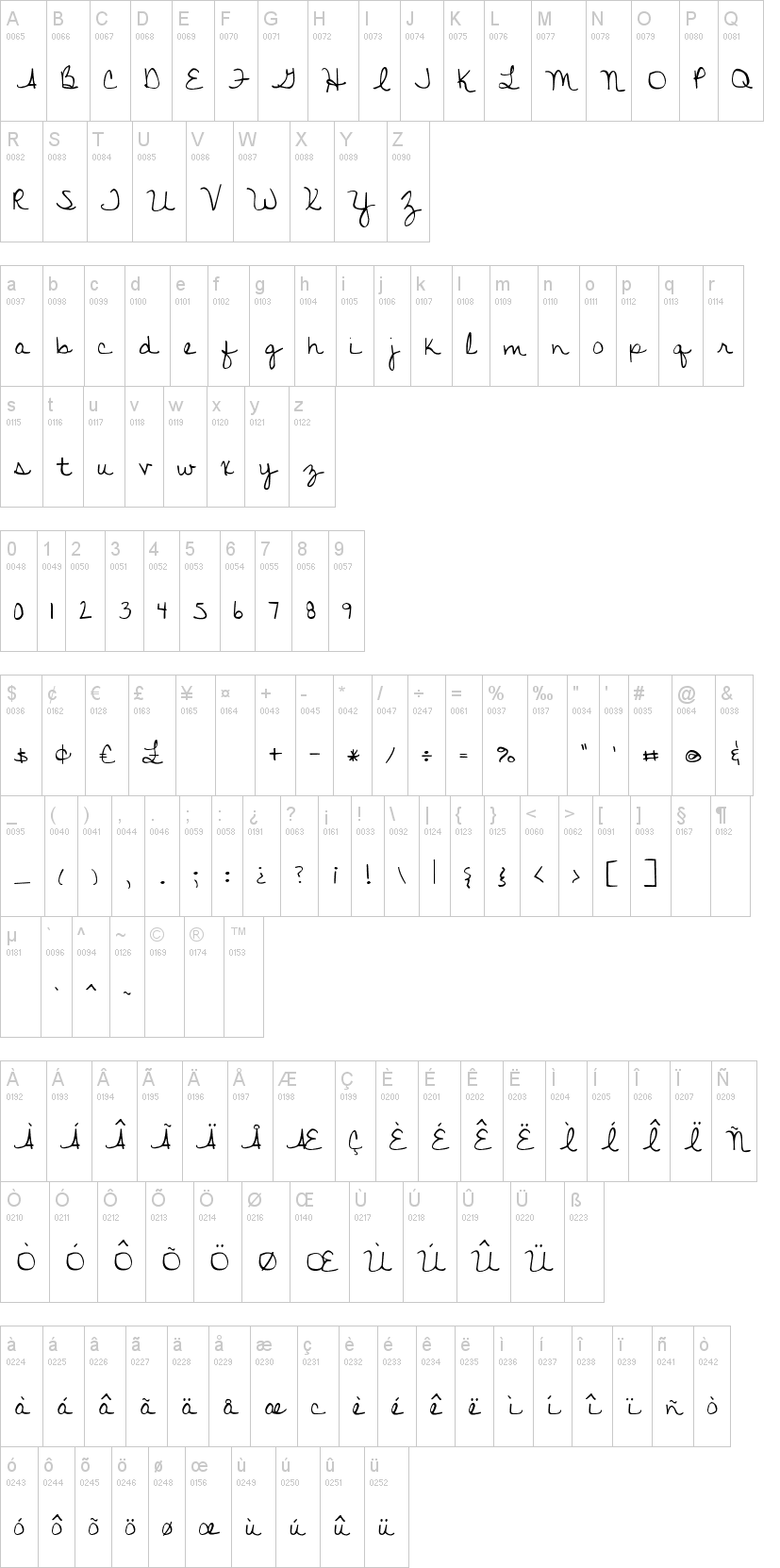
Discover Beauty
Discover Beauty字体是一款简洁、优雅的英文字体,它灵感源自经典的欧洲文字风格,具有清晰的细节和精致的字形,是一款极具现代感的字体。它可以用于各种各样的设计项目,尤其适合用于时尚、健康和美容行业的设计工作。它的字体特点使它成为一款非常受欢迎的字体,可以为您的设计项目带来极大的灵感。
Discover Beauty是一款非常不错的手写艺术字体,具有很好的视觉感,适合于文化类的宣传设计、商业类品牌的广告和产品包装设计以及个性化文字排版等较多场景。
Discover Beauty字符映射图